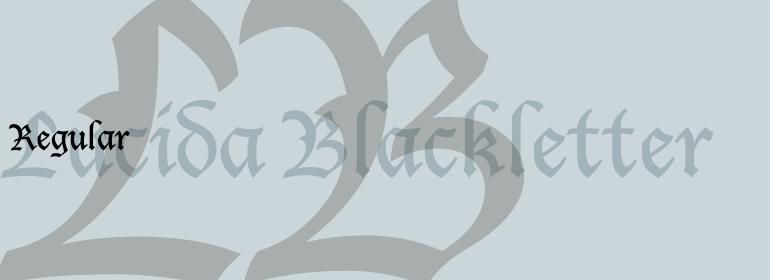
Lucida® Blackletter
Lucida® Blackletter,这款字体结构工整、笔画清晰,兼顾美观与易读性,适用于标题、正文、海报、包装、LOGO 等多种场景。字形优雅稳定,风格百搭耐看,适配日常排版与创意设计,让文字呈现更舒适、更具质感。Lucida® Blackletter一笔一画,皆是细节,以均衡的比例、流畅的线条打造舒适视觉体验,字形端正大气,风格简约现代。无论是商业设计、品牌宣传还是日常排版,都能轻松驾驭,让文字更有格调与力量。Lucida® Blackletter字体下载。